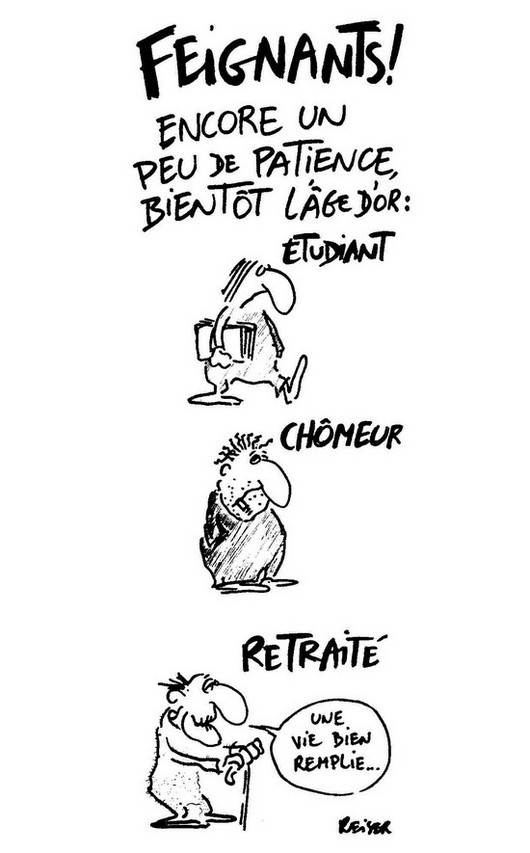
Ou moins sympathique : SUPPRIMONS LES RETRAITES !
Là, ça devient du Reiser !
J'avais commencé une collection de ce genre, c'était du temps du
regretté Lacroux - comme le temps passe ! C'était quasiment au début du
Web !... C'est ici :
Excellent, merci.
Ma préférée, et qui m'a valu nombre de faux signalement d'erreurs, est
la suivante :
MON MARI EST INTERNE À L'ASILE DE DAVE
L'accent sur le « à » lève l'ambiguïté sur « interne », qui n'est pas
"interné"...
Il manque cruellement.
Hors charte, sauf que même Reiser accentue, ici ;-)) :